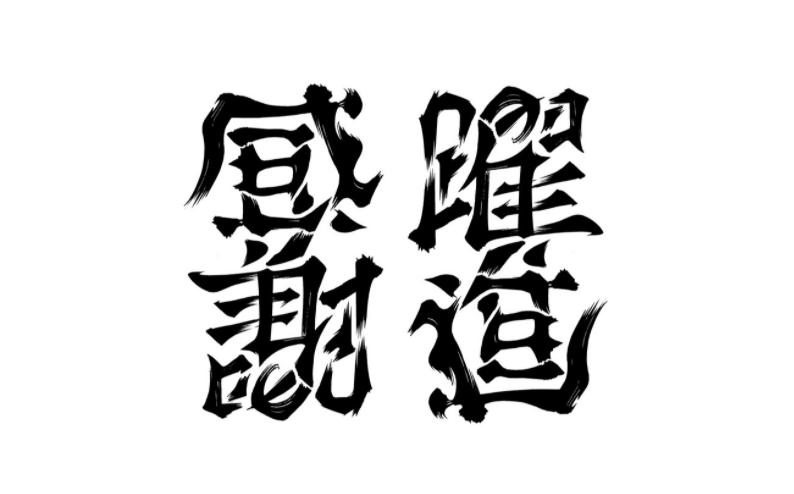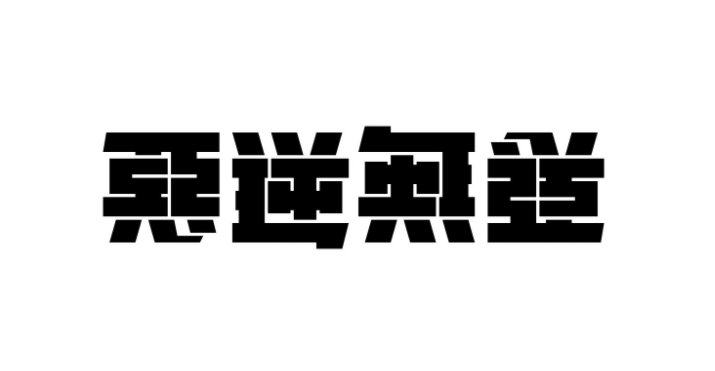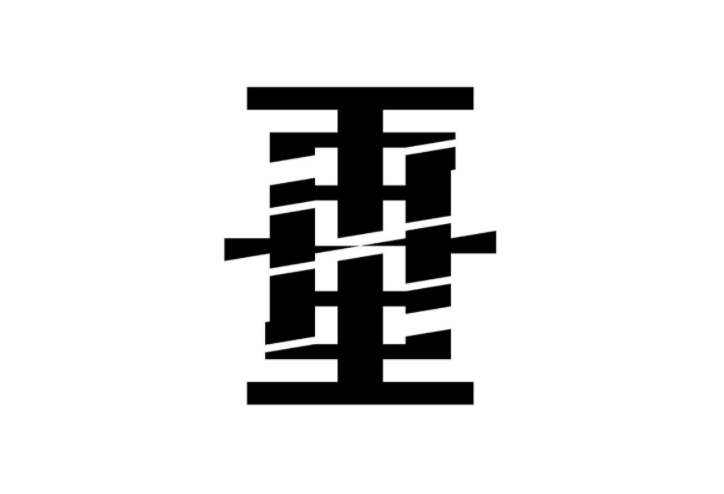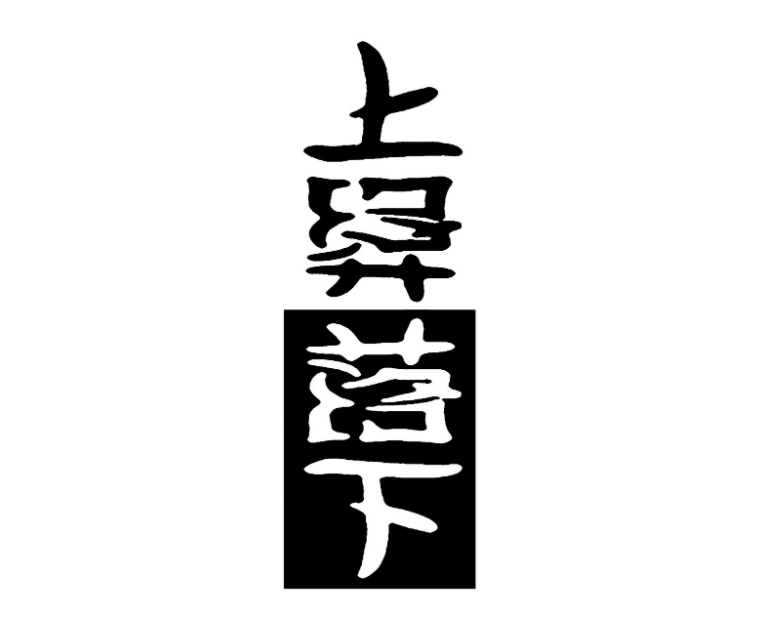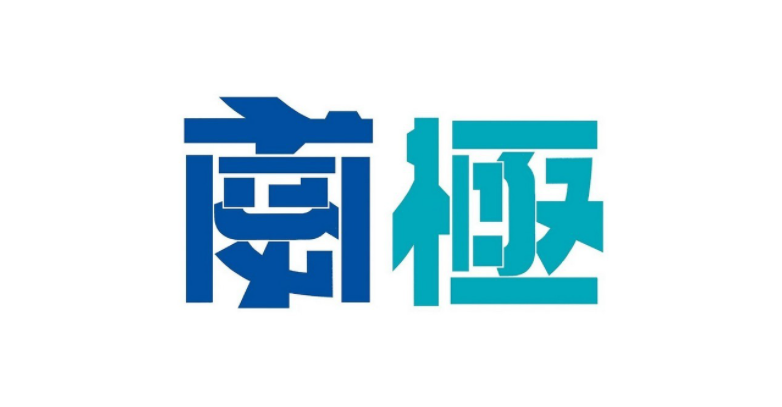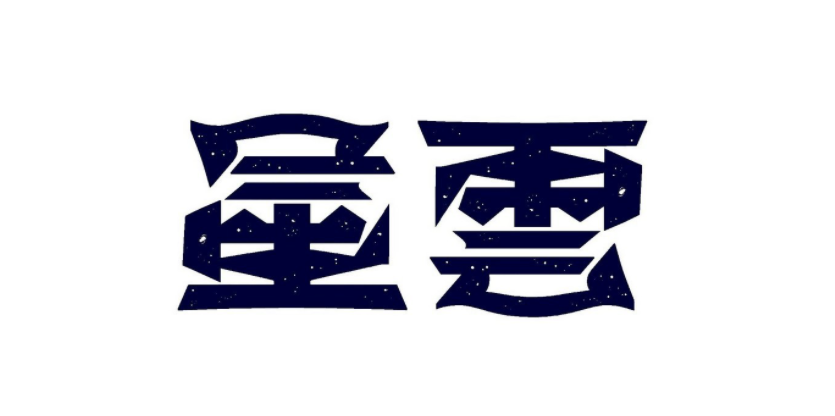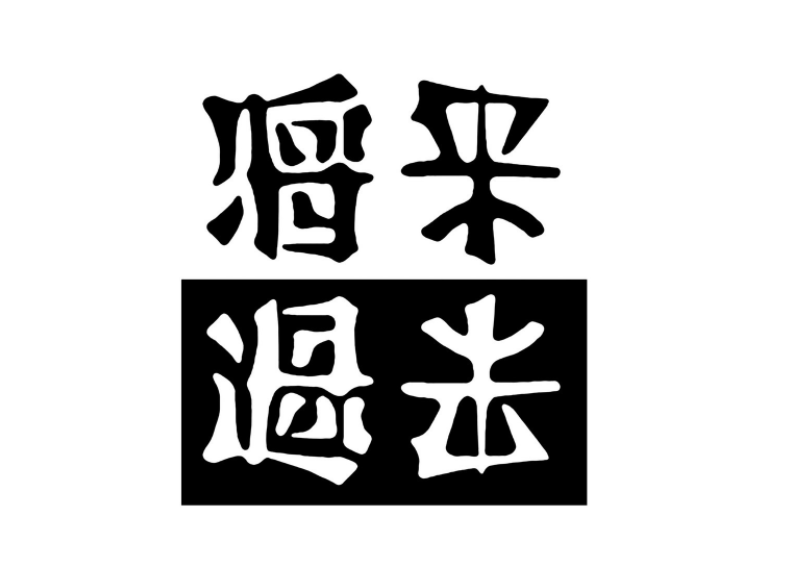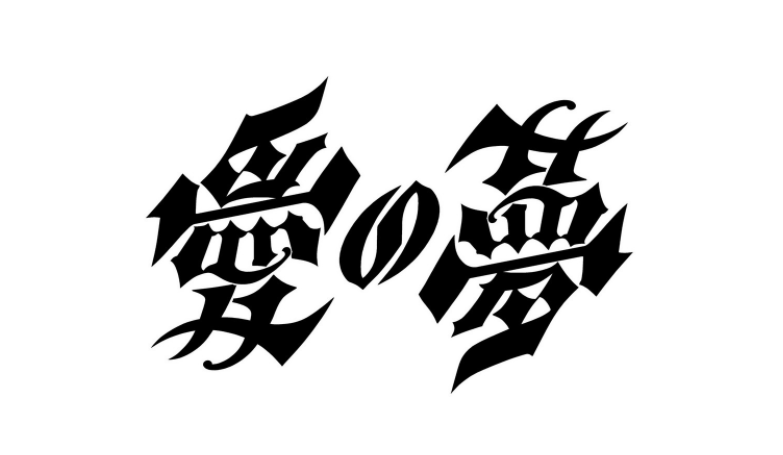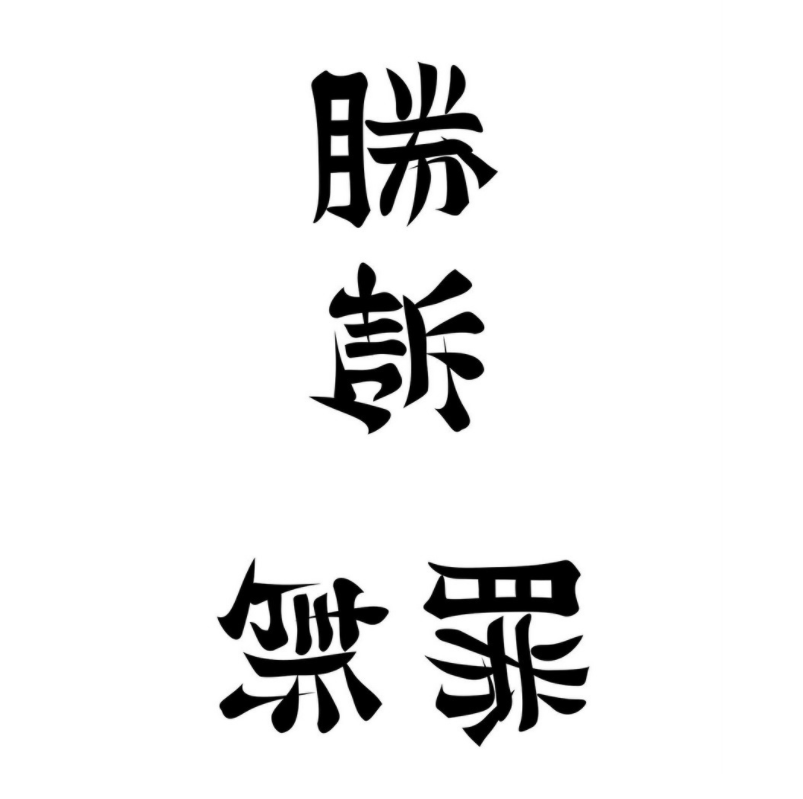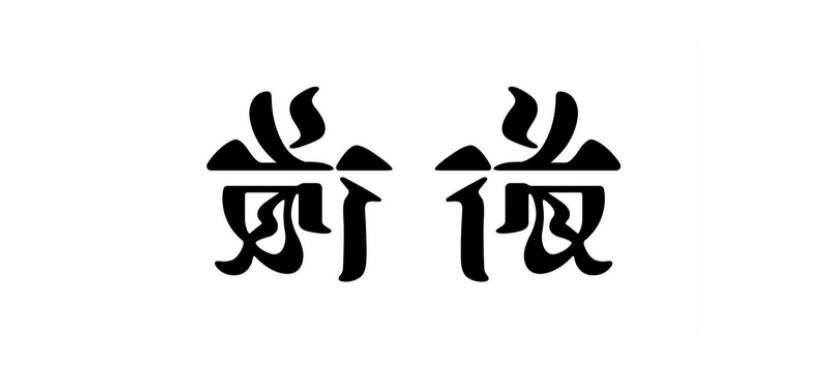
当字体设计自带“解谜性”,一看我就陷进去了……
大家都知道元宵节要猜灯谜,
但我今天想让你猜字谜,
没错,就是双向字设计,
最著名的就是日本设计师野村一晟,
他创作的文字艺术作品,非常有想法,
将双向字玩到出神入化,看得人叹为观止!
那么
除了双向字外
还有180°旋转、镜像
镜面对称、反转等旋转式文字创作
你准备好了吗?
下面进入观摩(解谜)时间
『分合』
分割“合”就会变成“分”。
『感謝/躍進』
将“感謝”旋转180°
就会变成“躍進”
『喧嚣/静寂』
“喧嚣”180°旋转“静寂”
『悪逆無道』
将“悪逆”旋转180°
就会变成“無道”
『谜/解』
180°旋转角图
『死亡/来世』
把“去世”转180°就能读作“来世”
『再生』
180°旋转角度图
即使翻转字面也会再生
『纵向横向』
90度旋转,将“纵”横倒后变成“横”字形。
『上昇/落下』
镜面对称角度图
上升相对的单词是下降
使用垂直排列的镜面对称
『南極』
90度旋转角图
南极点是南纬90度
自转天体的最南端
『色即是空』
180°旋转角图
『収支』
回旋型字
『倒过来!』
180°旋转对称的立体图。
『星雲』
180°旋转角图
『回转寿司』
180°旋转角图
『将来/過去』
镜面对称字
『愛の夢』
180度旋转字
语句来自佛朗兹列表中的“爱之梦”
把以前画的东西参考成了古典的黑色信风格
装饰的字体非常适合
『勝訴/無罪』
将“勝訴”旋转90°后
就会变成“無罪”
很有趣
『前 後』
90度旋转角图
镜像字
“前”和“后”是硬币的正反面
这是一个符合各自意思的噱头文字
『包』
反转角度图
用底片包起来,用正片包起来
『文字』
180度旋转
重复也是同样的字面
远古时代的人在自己的皮肤上写下了汉字
『立体』
立体图图案
重复的话也会变成同样的字面
『歩行・走行』
左右镜像的角度图
『飛 鳥』
反转的旋转式图
斜着配置的话就是镜像型
『水/火』
由于颜色不同,感知也发生了变化
『将来/過去』
“将来”和“过去”是镜面对称的
『陰陽』
“阳”的影子变成“阴”的
『理解/誤解』
180度旋转
无论从哪一方面看都是理解和误解
『送信/受信』
镜像字形,使用箭头图标
『達磨』
180°旋转角图
倒立起来看也是同样的字形
适合装饰性强的字体
『新年快乐/Happy New Year』
180°旋转。把日语的问候语颠倒过来就是英语的问候语。